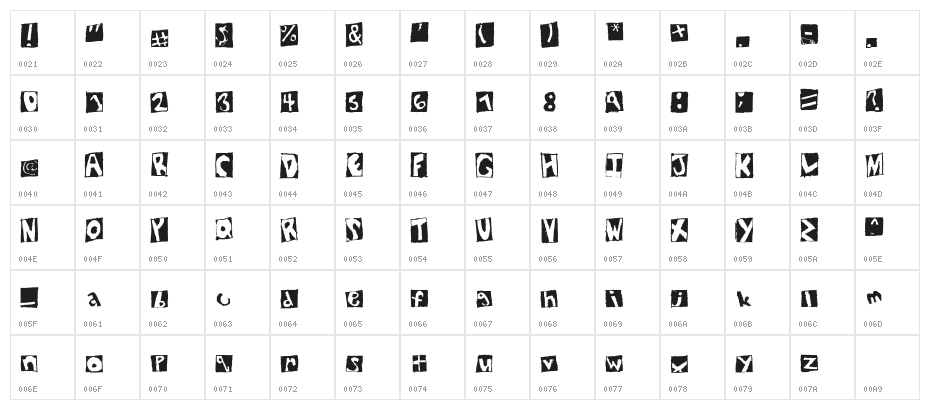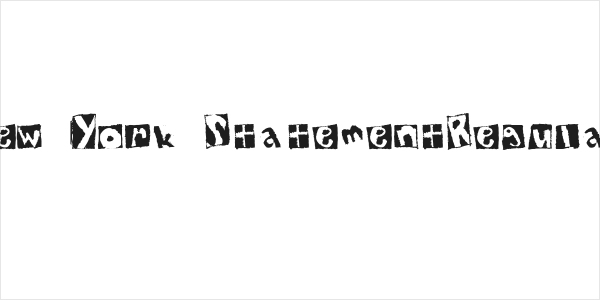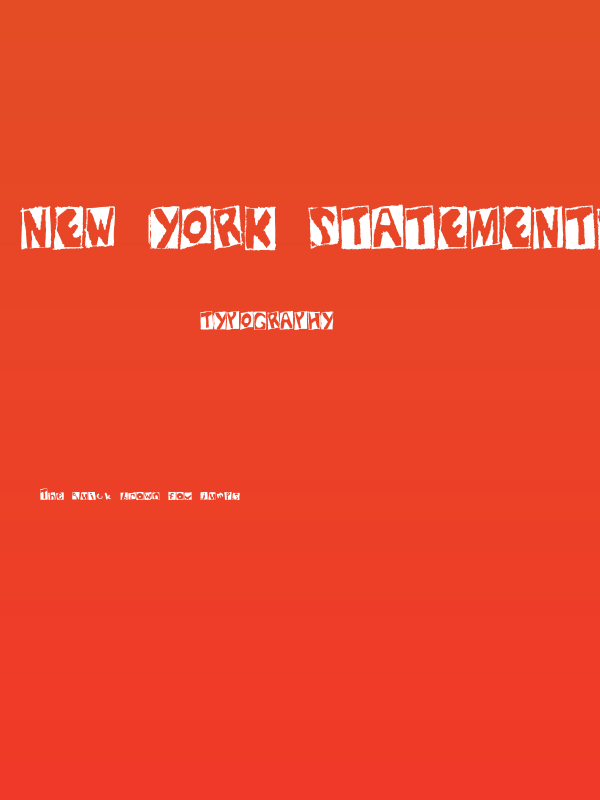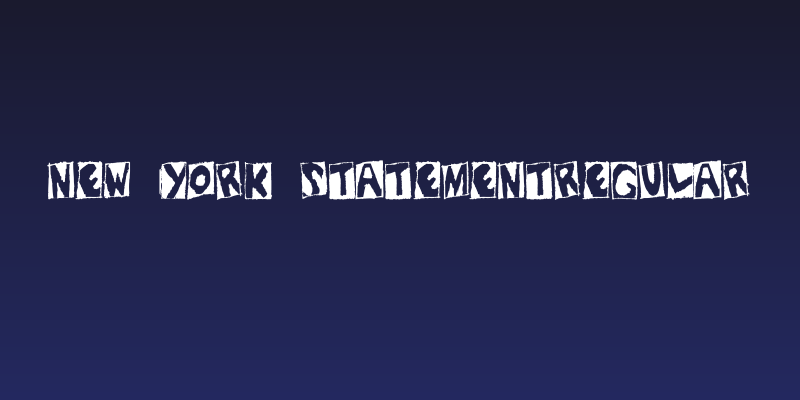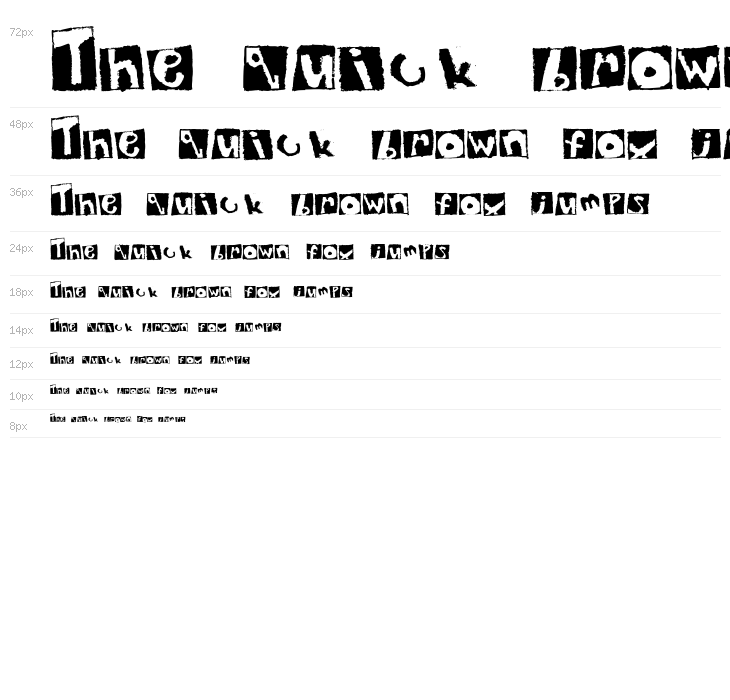
New York StatementRegular Font
| Stile generale | Modern, Edgy |
| Progetti proposti | Ideal for posters, album covers, and designs needing an edgy, urban vibe. |